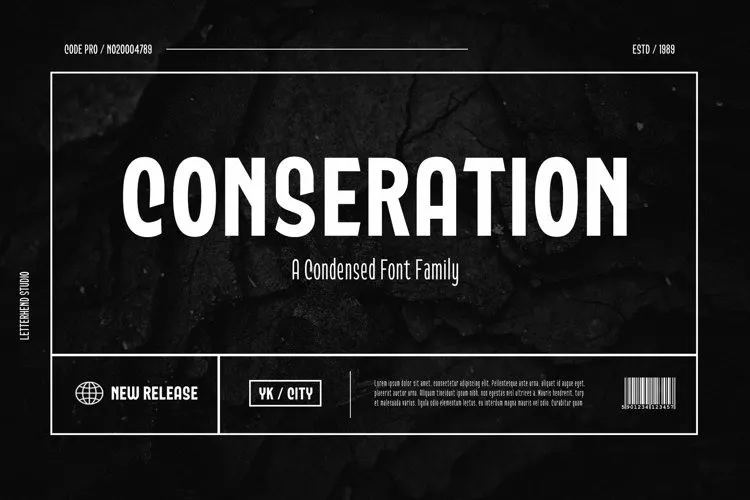
Esta fonte é uma versão sofisticada do tipo sans serif. Ela foi criada pelo estúdio de letras Letterhend Studio. Com cinco tipos diferentes – regular, leve, bold, semi e médio – você pode escolher o que melhor atende às suas necessidades. Apesar de ser elegante e luxuosa, mantém um toque divertido e descontraído. Esta fonte foi projetada especificamente para aplicação em logomarcas e outros formatos formais como convites, etiquetas, logos, revistas, livros, cartas de casamento, embalagens, moda, maquiagem, materiais de estabelecimento ou qualquer tipo de propósito publicitário. E se você está procurando por uma fonte que combine elegância com leveza e diversão, esta é a escolha perfeita.